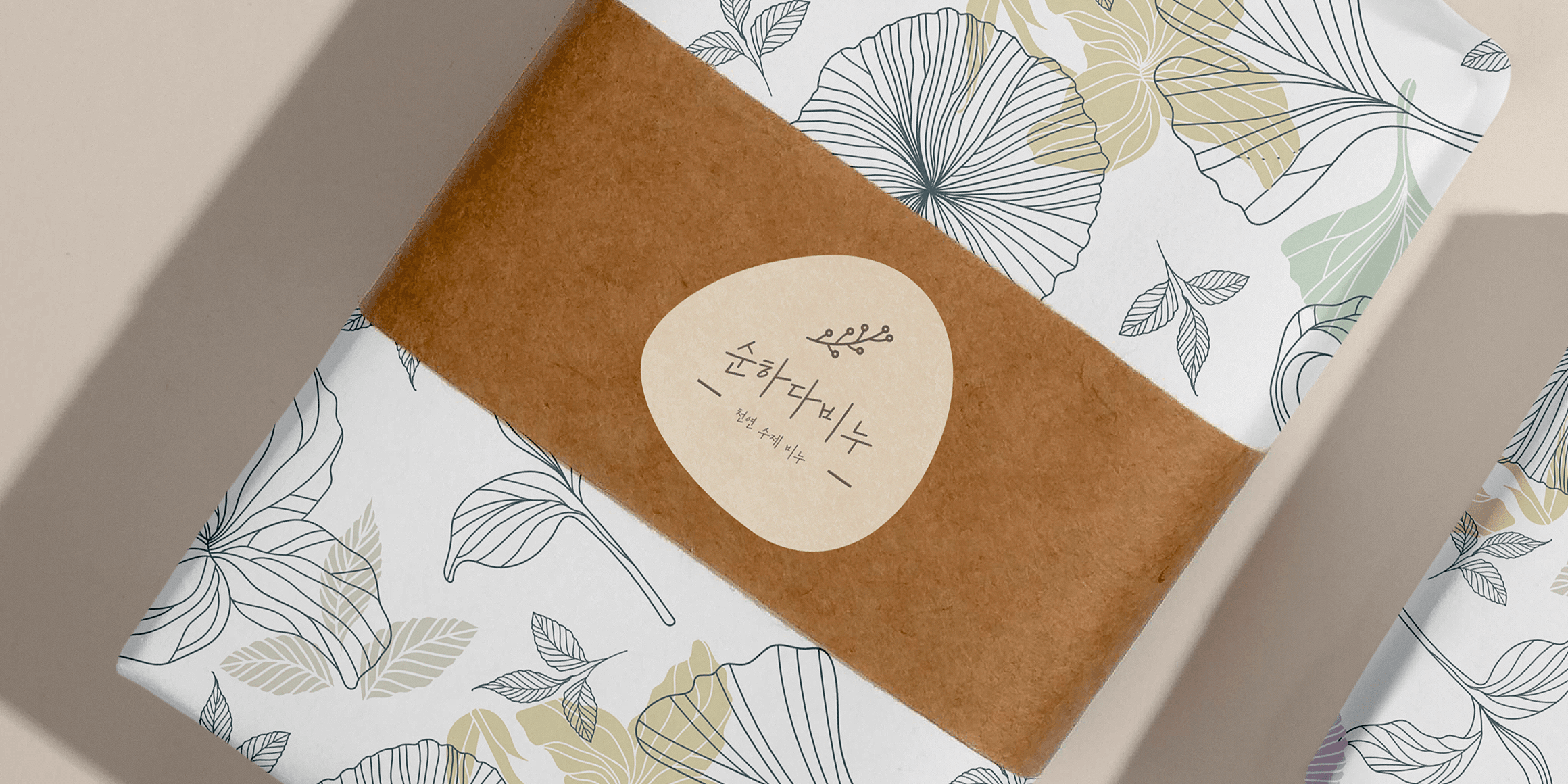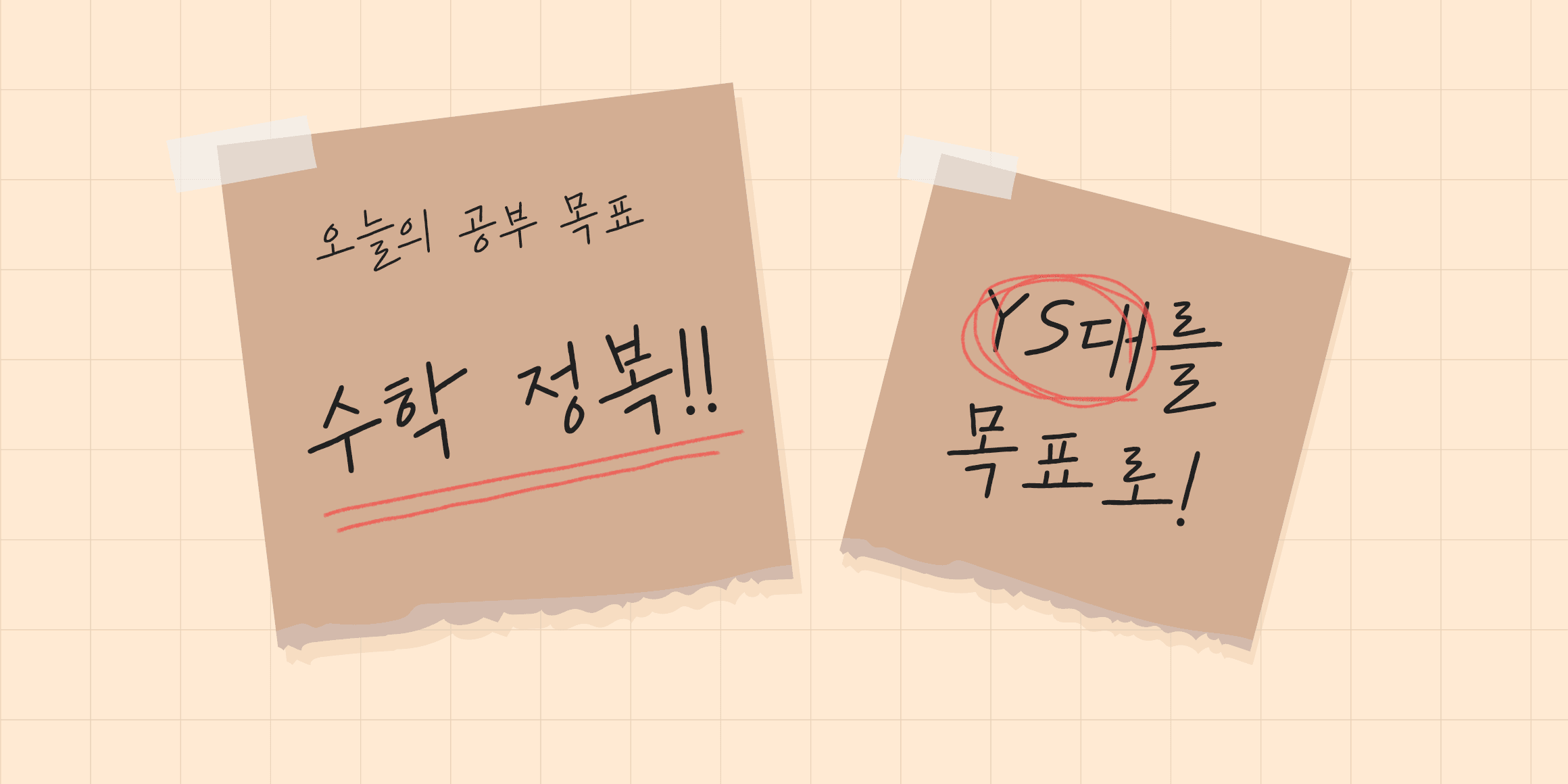
에필로그
인문학적 감성을 담은 세리프 계열
Design210
인문학적 감성을 담은 세리프 계열 서체로, 우아하면서도 친근한 분위기를 제공하여 책표지, 에세이 본문, 문화 콘텐츠 타이틀 등에 적합합니다. 획의 시작과 끝에 미세한 테우림(세리프)이 있어 글줄이 부드럽게 연결되고, 적절한 대비로 가독성을 유지하면서도 고급스러운 느낌을 더합니다. 문학적·예술적 톤을 강조하고 싶은 프로젝트에 추천합니다.